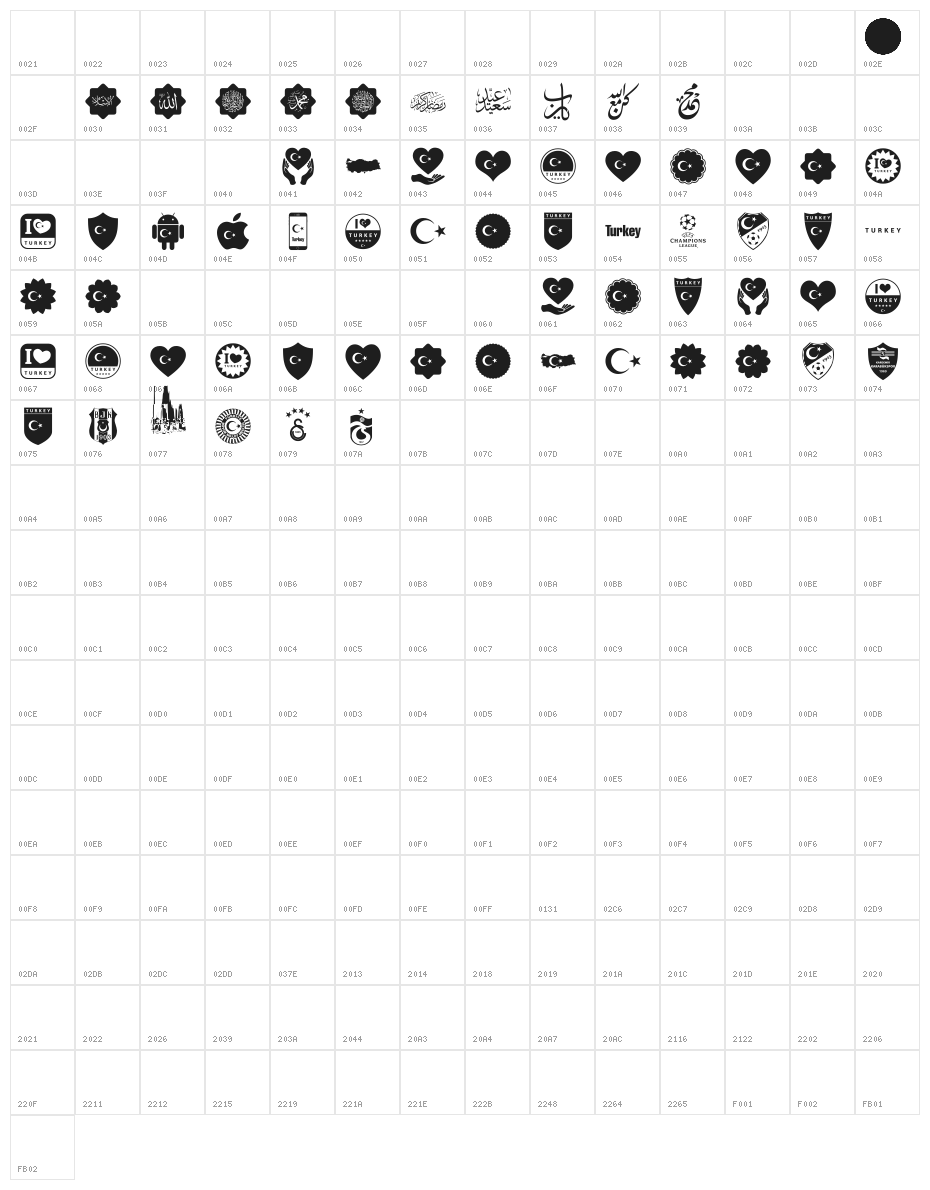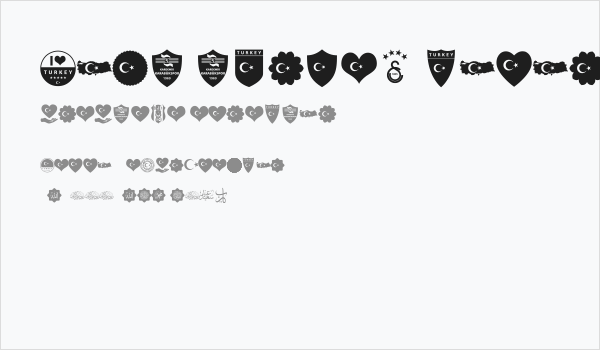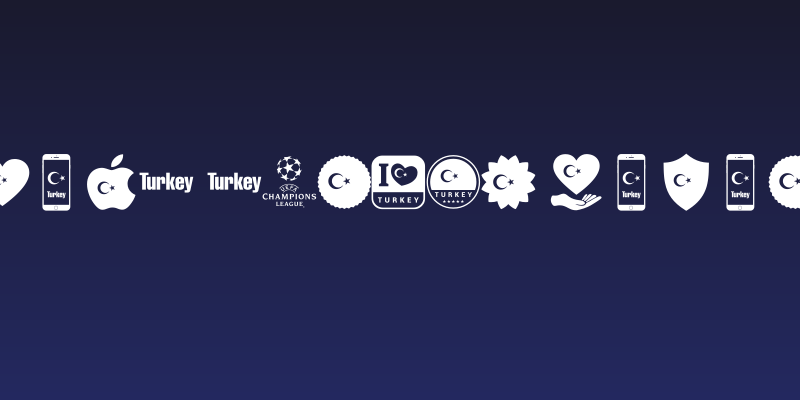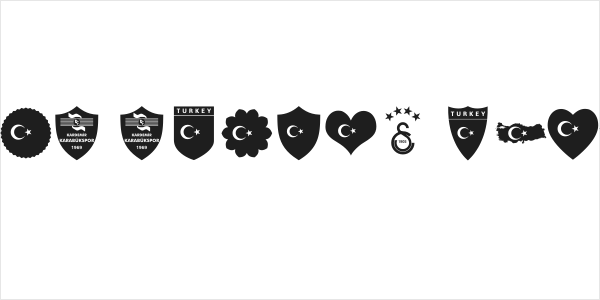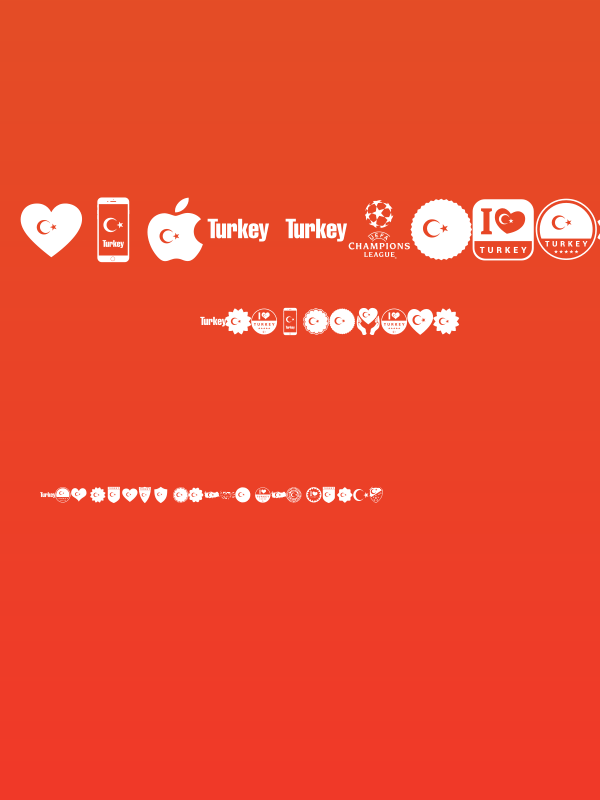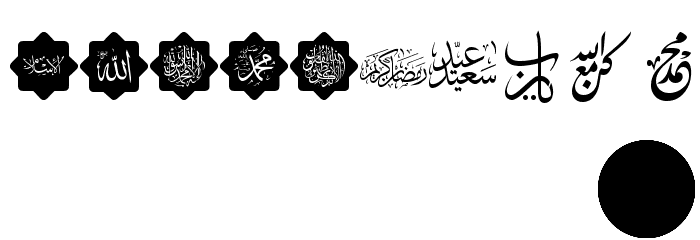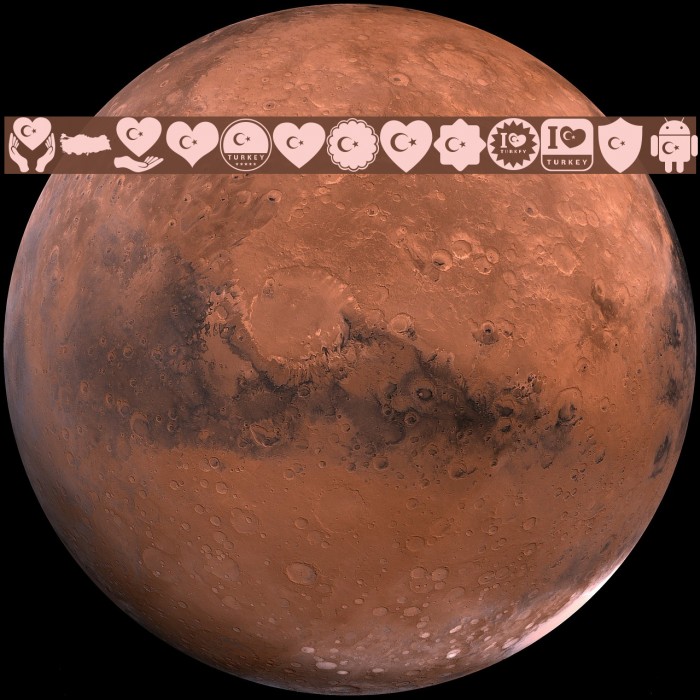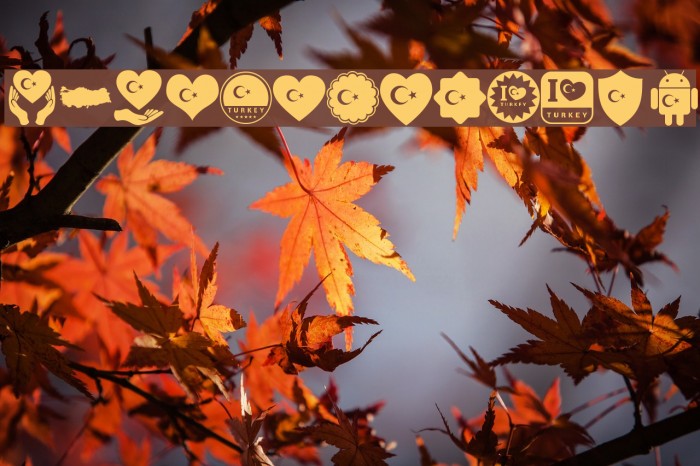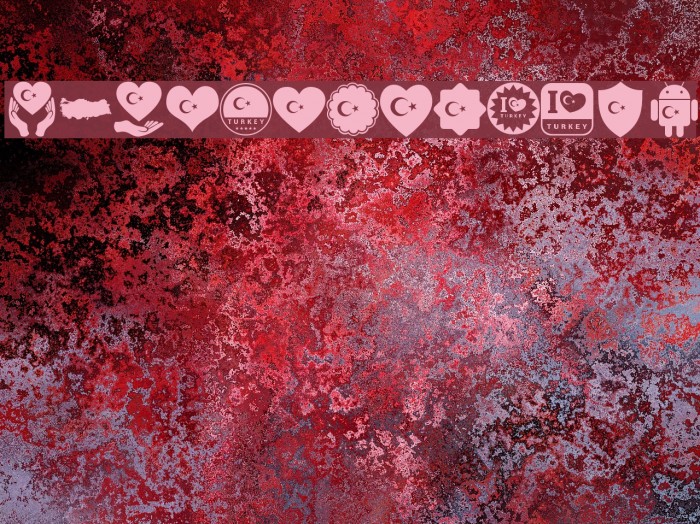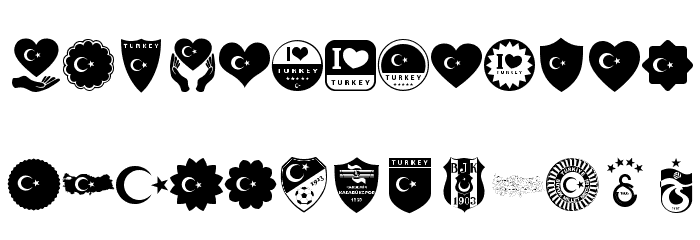
font turkey color Font
✎ Calligraphic
| Kategorien | Calligraphic |
| Anwendungsfall | Logos, Merchandise, Cultural Events |
| Vorgeschlagene Projekte | Ideal for cultural events, tourism materials, patriotic merchandise, or themed graphic design projects. |
| Autor | Fonts by Måns Grebäck |